멋진 싸인은 한 번 보면 기억에 남아야 해요. 단순하면서도 강렬한 인상을 남기는 싸인이 가장 좋은 싸인이죠! 🎯
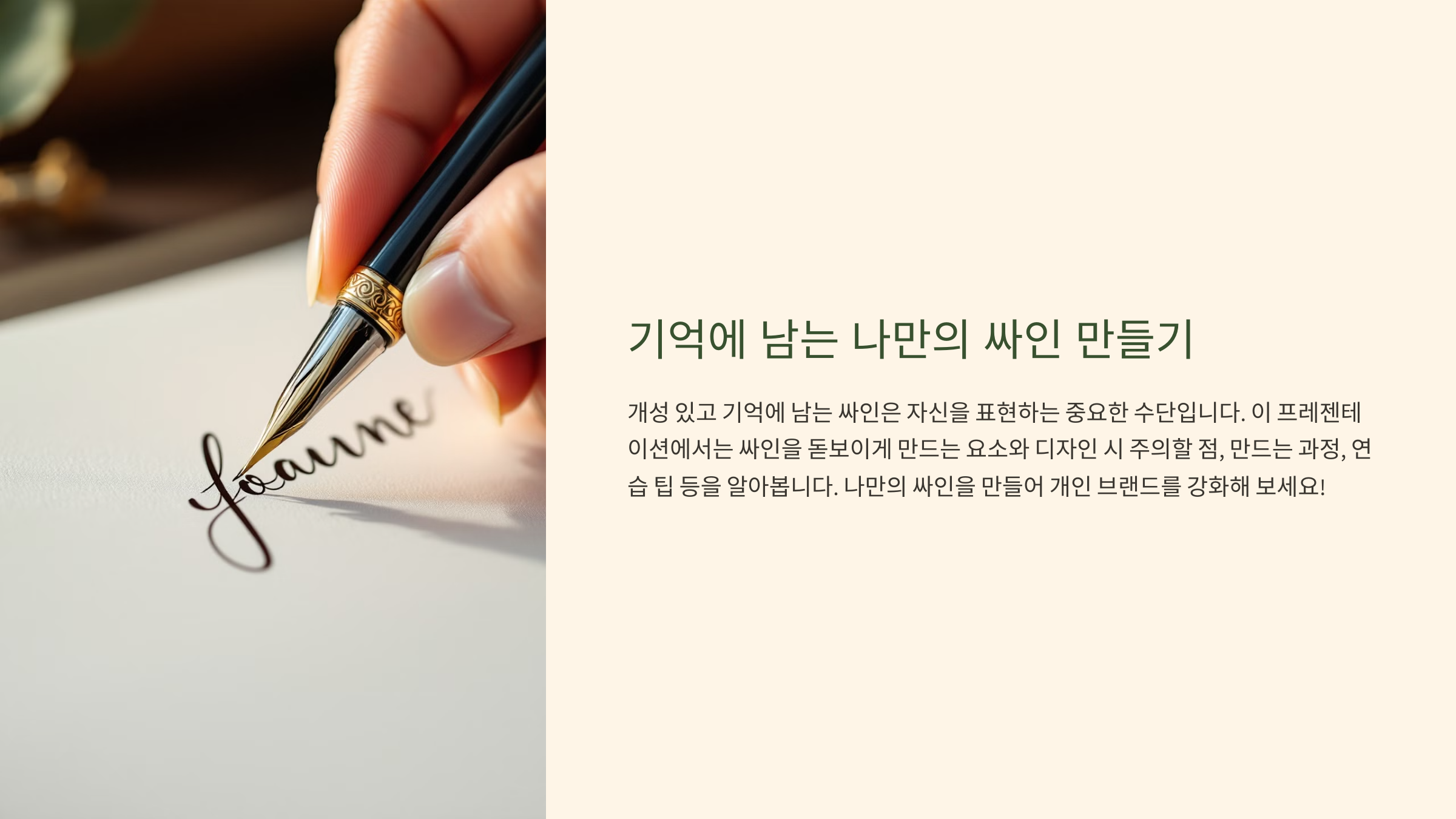
내가 생각했을 때, 기억에 남는 싸인은 단순함 + 개성이 조화를 이루어야 해요. 너무 복잡하면 실전에서 사용하기 어렵고, 너무 단순하면 개성이 부족할 수 있어요. ✍
그럼 한 번 보면 절대 잊히지 않는 싸인 디자인 비법을 배워볼까요? 🚀
기억에 남는 싸인의 특징 🖊
멋진 싸인은 한 번 보면 쉽게 잊히지 않아야 해요! 단순한 서명이 아니라, 나를 대표하는 상징적인 디자인이 되어야 하죠. 🌟🔹 단순하지만 강렬한 디자인 너무 복잡하면 기억하기 어렵고, 실전에서 빠르게 싸인하기 힘들어요. 짧고 간결하면서도 개성 있는 스타일을 유지하는 것이 중요해요.
🔹 독창적인 요소 포함 이니셜을 변형하거나, 기호(하트❤, 별⭐, 번개⚡ 등)를 추가하면 더 특별한 느낌을 줄 수 있어요. 🎨
🔹 자연스럽고 부드러운 흐름 싸인은 너무 뻣뻣하게 만들면 오히려 쓰기 어려워요. 자연스럽게 이어지는 필기체 스타일이 더욱 효과적이에요. ✍
📌 기억에 남는 싸인의 핵심 요소 🔍
요소 설명 단순한 구조 복잡하지 않고 짧고 간결해야 함 독창적인 요소 이니셜 변형, 기호(⭐,❤ 등) 추가 자연스러운 흐름 필기체 스타일로 부드럽게 연결 한눈에 알아볼 수 있음 너무 복잡하지 않고 명확한 형태 유지 이제 싸인을 더 돋보이게 만드는 요소를 알아볼까요? ✨
싸인을 더 돋보이게 만드는 요소 ✨
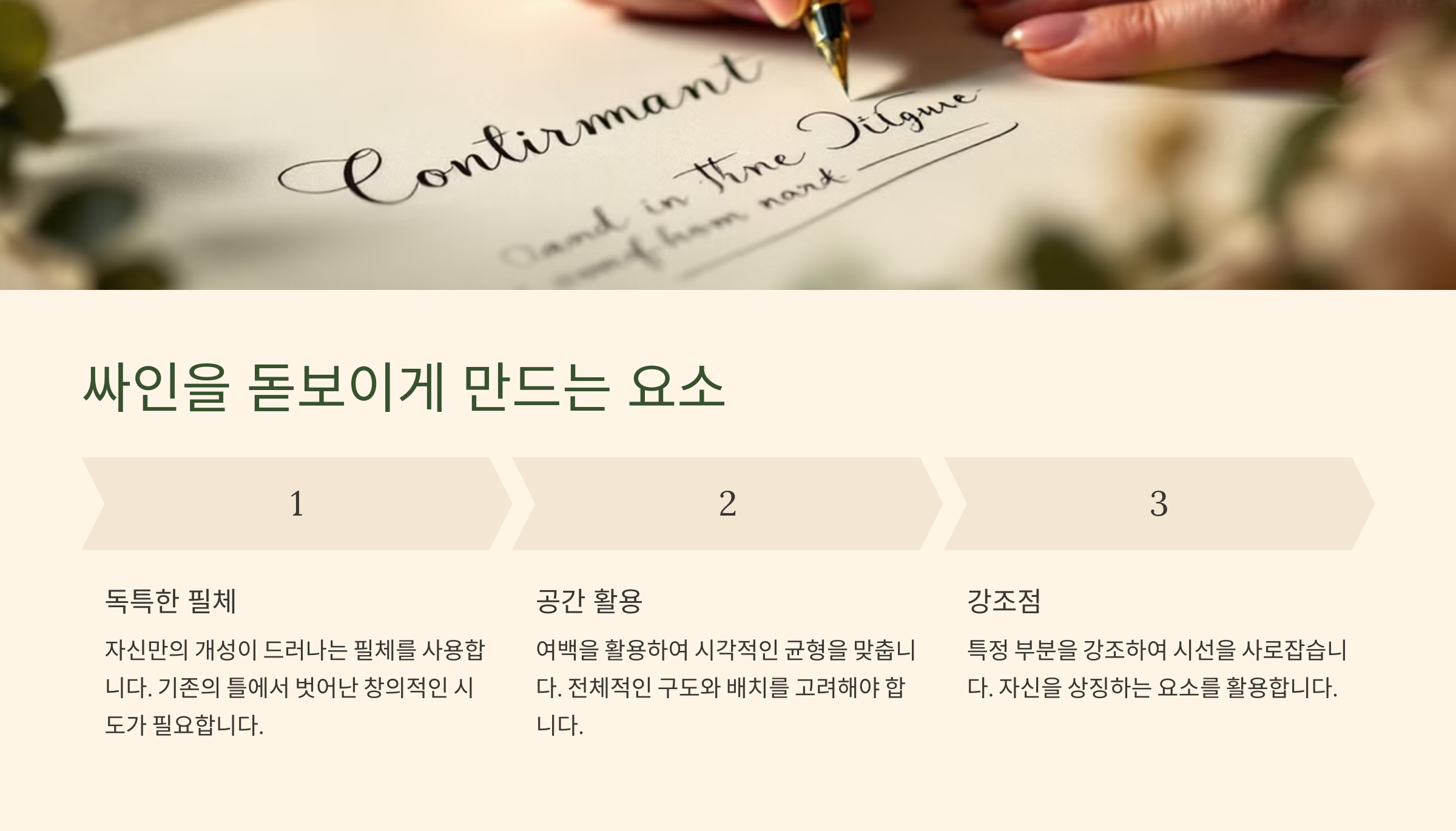
멋진 싸인은 단순히 이름을 쓰는 것이 아니라, 하나의 디자인 작품처럼 개성을 담아야 해요. 작은 차이만 줘도 싸인의 분위기가 완전히 달라질 수 있어요! 🎨🔹 이니셜을 강조하라! 이름 전체를 쓰기보다 이니셜을 변형하면 더 강렬한 인상을 남길 수 있어요. 예를 들어, ‘J.K’처럼 간단하게 정리하면 기억하기 쉬워요.
🔹 특별한 기호 추가하기 하트❤, 별⭐, 화살표➡ 같은 심볼을 싸인에 포함하면 개성이 더욱 살아나요! BTS 멤버들의 싸인처럼 간단한 아이콘을 추가해도 효과적이에요. ✍
🔹 속도감과 자연스러움 유지하기 싸인은 빠르게 써야 할 때가 많아요! 너무 복잡하면 실전에서 사용하기 힘드니, 필기체를 활용해 부드럽고 자연스럽게 연결해 보세요. ⏳
📌 싸인을 더욱 특별하게 만드는 요소 💡
요소 설명 이니셜 강조 이름 대신 첫 글자만 강렬하게 표현 기호 추가 하트❤, 별⭐, 화살표➡ 등 개성 표현 속도감 빠르게 써도 알아볼 수 있는 디자인 자연스러운 흐름 필기체 활용하여 부드럽게 연결 이제 실제로 기억에 남는 스타일별 싸인 예시를 살펴볼까요? 🔎
스타일별 기억에 남는 싸인 예시 🔎
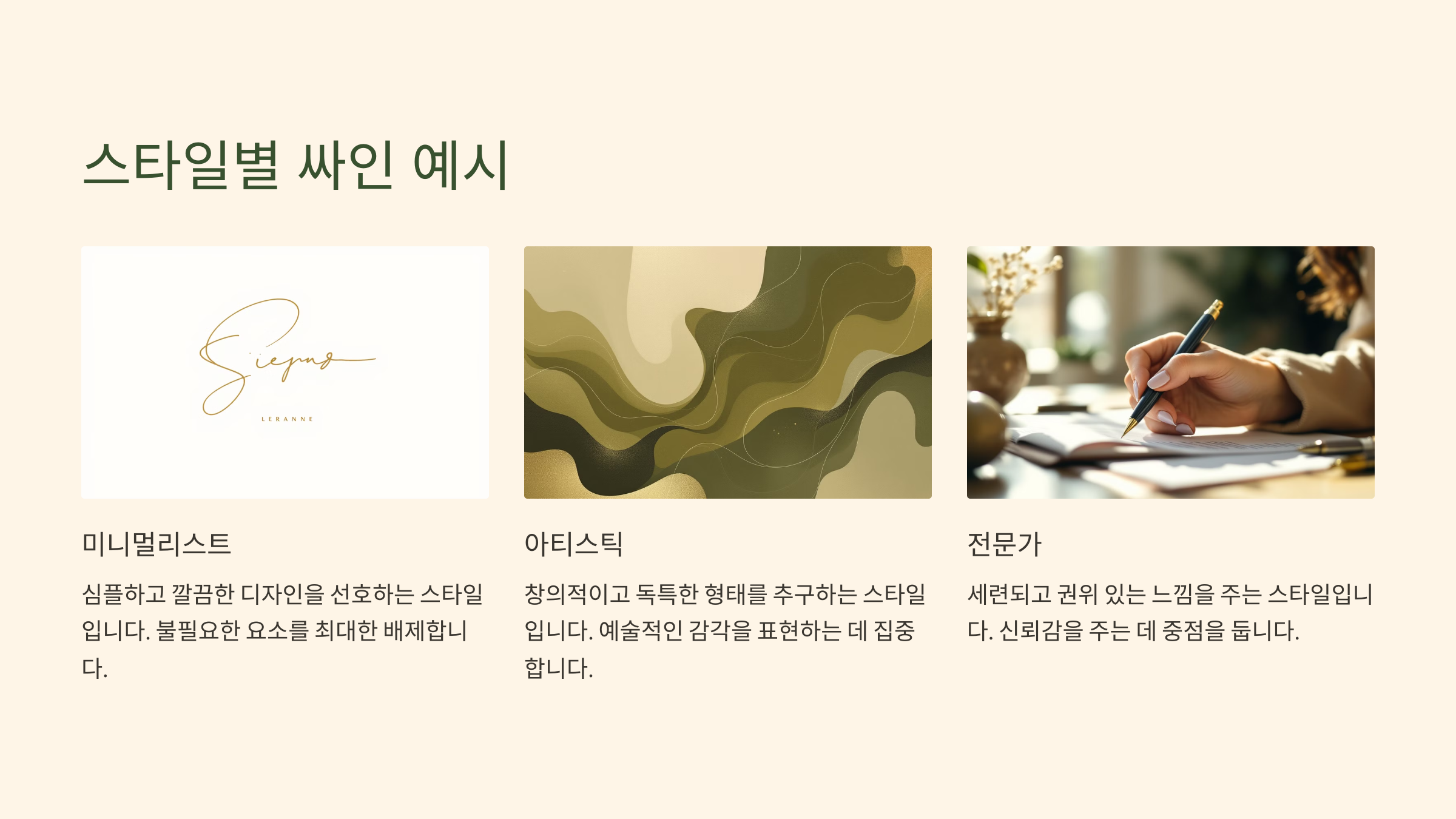
싸인의 스타일은 사람마다 다 달라요. 어떤 스타일을 선택하느냐에 따라 분위기와 인상이 확 달라질 수 있죠. 아래 스타일별 싸인 예시를 보면서 나에게 맞는 스타일을 찾아보세요! ✍
🔹 이니셜형 싸인 이름 전체를 쓰는 대신, 이니셜만 강조하는 스타일이에요. 예를 들어, 'J.H.', 'T.S.', 'RM' 같은 간결한 싸인이 여기에 속해요. ✅ 깔끔하고 세련된 느낌을 주고, 빠르게 싸인할 수 있어요.
🔹 필기체형 싸인 자연스럽게 흐르는 필기체 스타일이에요. 테일러 스위프트의 싸인처럼 부드럽고 우아한 느낌을 줄 수 있어요. ✅ 서명이 필요한 공식 문서에서 활용하기 좋아요.
🔹 그래픽형 싸인 싸인 속에 작은 그림 요소(별⭐, 하트❤, 번개⚡ 등)가 들어가 있는 스타일이에요. 예를 들어, G-DRAGON의 싸인은 독특한 기호와 곡선을 활용해 더욱 개성이 강해요. ✅ 연예인이나 아티스트들이 많이 사용하는 스타일!
📌 스타일별 기억에 남는 싸인 예시 📜
스타일 특징 추천 대상 이니셜형 짧고 강렬한 인상, 간결한 디자인 비즈니스 전문가, 공문서 서명 필기체형 부드럽고 우아한 흐름, 자연스러움 예술가, 디자이너, 작가 그래픽형 개성 넘치는 그림 요소 포함 연예인, 크리에이터, 인플루언서 이제 싸인을 디자인할 때 주의해야 할 점을 살펴볼까요? ⚠
싸인 디자인 시 주의할 점 ⚠
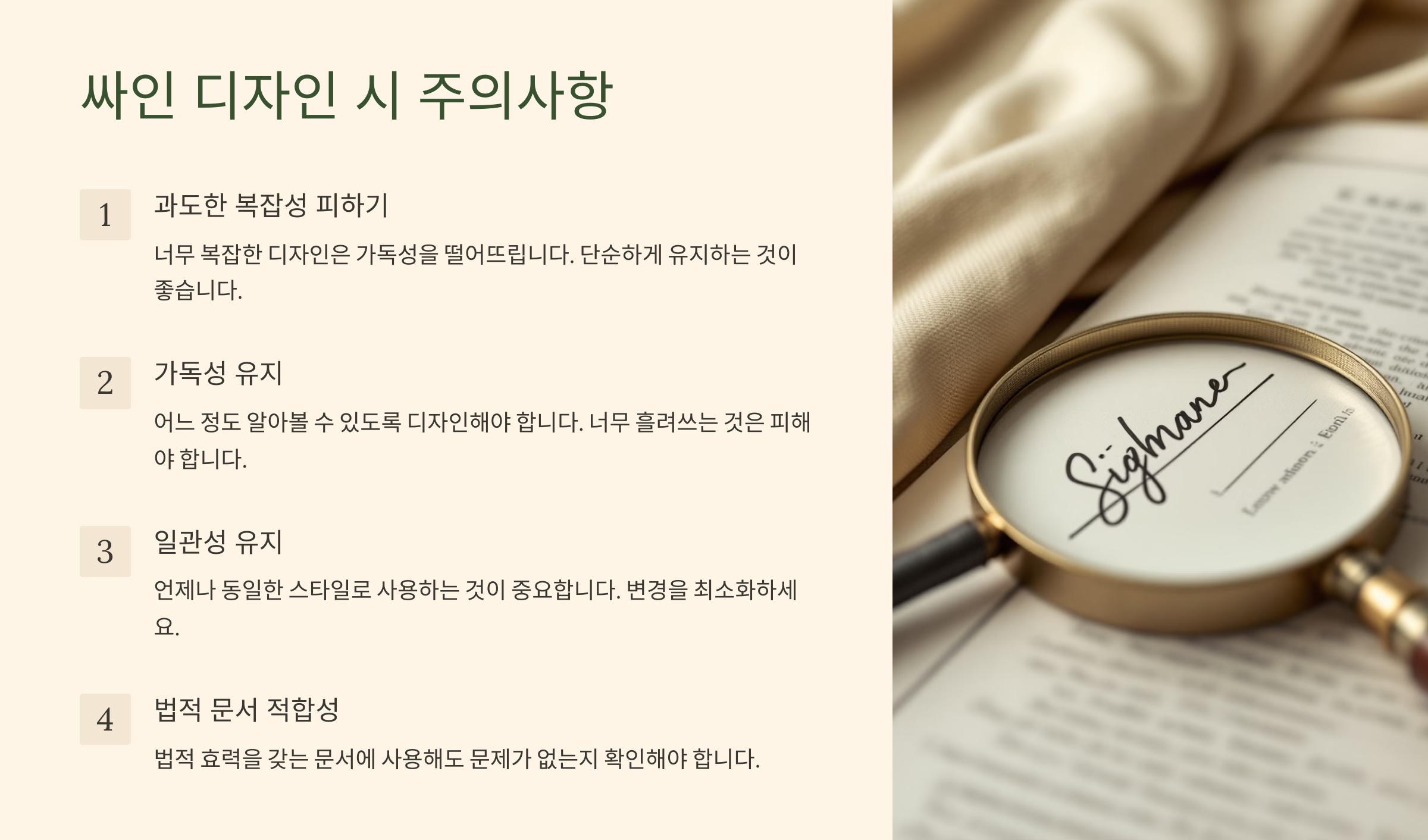
멋진 싸인을 만들기 위해서는 주의해야 할 몇 가지 요소가 있어요. 디자인이 너무 복잡하거나, 실용성이 떨어지면 오히려 불편할 수 있죠! ✍
🔹 너무 복잡한 싸인 피하기 디자인이 지나치게 복잡하면 빠르게 싸인하기 어렵고, 인쇄 시 잘 보이지 않을 수도 있어요. ✅ 단순하면서도 개성이 있는 것이 중요해요!
🔹 읽기 어려운 글씨체 지양하기 너무 독특한 필체를 사용하면 다른 사람이 알아보기 어렵거나, 본인조차 나중에 알아보기 힘들 수도 있어요. ✅ 적당히 알아볼 수 있는 디자인이 좋아요.
🔹 너무 작은 싸인은 피하기 싸인이 너무 작으면 공식 문서나 계약서에서 제대로 보이지 않을 수도 있어요. ✅ A4 용지, 명함, 메모지 등에 테스트하면서 적절한 크기를 찾아보세요.
📌 싸인 디자인 시 피해야 할 실수 ❌
실수 설명 복잡한 디자인 너무 많은 선과 기호를 사용하면 읽기 어려움 읽기 어려운 글씨 너무 기울이거나 변형하면 알아보기 힘듦 너무 작은 크기 공식 문서에서 잘 보이지 않을 가능성 있음 일관성 부족 싸인할 때마다 모양이 달라지는 문제 발생 이제 기억에 남는 싸인을 만들기 위한 5단계 과정을 알아볼까요? 🏆
기억에 남는 싸인 만드는 5단계 과정 🏆
한 번 보면 기억에 남는 싸인을 만들기 위해서는 단계별로 체계적인 연습이 필요해요! 이제 아래 5단계 과정을 따라 하면 나만의 개성 있는 싸인을 완성할 수 있어요. ✍
🔹 1단계: 기본 형태 정하기 이름을 풀네임으로 쓸지, 이니셜을 강조할지 먼저 결정하세요. ✅ 'J.Kim'처럼 짧고 강렬한 스타일이 좋을 수도 있어요.
🔹 2단계: 스타일 선택하기 필기체, 직선형, 곡선형 등 원하는 스타일을 선택하세요. ✅ 자연스럽게 연결되는 필기체 스타일이 기억에 남기 좋아요.
🔹 3단계: 기호 & 장식 추가하기 별⭐, 하트❤, 번개⚡ 같은 작은 기호를 넣어 싸인에 개성을 더해보세요. ✅ 너무 많은 기호를 넣으면 복잡해 보일 수 있으니 적절히 활용!
🔹 4단계: 크기와 속도 테스트 A4 용지, 명함, 메모지 등 다양한 크기에 싸인을 연습하면서 크기를 조절해 보세요. ✅ 싸인이 빠르게 써도 자연스럽게 보이도록 연습하는 게 중요해요!
🔹 5단계: 꾸준히 연습하기 최종적으로 선택한 스타일을 반복 연습하세요. 일관된 형태를 유지하는 것이 중요해요! ✅ 눈 감고 싸인을 해보거나, 빠르게 써보면서 실전 감각을 익혀보세요. ⏳
📌 기억에 남는 싸인 만드는 5단계 과정 🎯
단계 연습 방법 1단계 이름을 풀네임 또는 이니셜 중 선택 2단계 필기체, 곡선형 등 원하는 스타일 결정 3단계 별⭐, 하트❤ 같은 기호를 추가할지 결정 4단계 다양한 크기와 속도로 싸인 테스트 5단계 최종 스타일을 정하고 반복 연습 이제 싸인 연습을 더 효과적으로 할 수 있는 실전 꿀팁을 알아볼까요? 🚀
싸인 연습을 위한 실전 꿀팁 🚀
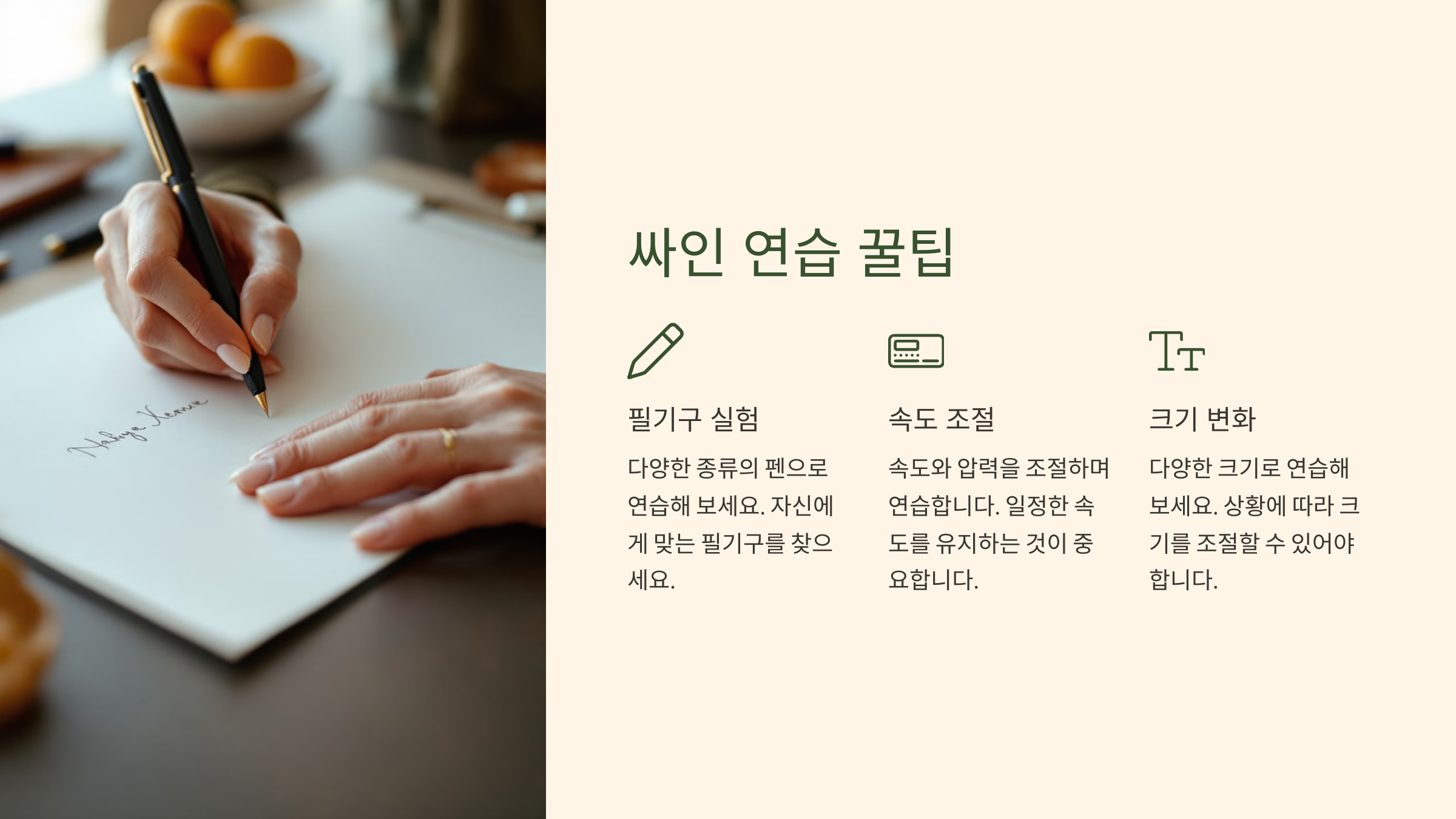
싸인은 단순히 디자인하는 것보다, 실제로 빠르게 싸인을 할 수 있도록 연습하는 과정이 중요해요! 아래 실전 꿀팁을 따라 하면 더욱 자연스럽고 멋진 싸인을 만들 수 있어요. ✍
🔹 거울을 보면서 연습하기 싸인을 하면서 거울을 통해 보는 시각도 중요해요. 다른 사람이 봤을 때 어떤 느낌인지 체크해보세요. 👀
🔹 눈 감고 싸인해보기 눈을 감고 싸인을 해보면 손이 자연스럽게 기억하는 싸인을 만들 수 있어요. ✅ 익숙해질 때까지 감각적으로 연습해보세요!
🔹 속도 조절하며 연습하기 너무 천천히 하면 실전에서 시간이 오래 걸리고, 너무 빠르면 알아보기 어려울 수 있어요. ✅ 적절한 속도를 찾으면서 연습해보세요. ⏳
🔹 다양한 크기로 싸인해보기 A4 용지, 명함, 포스트잇 등에 싸인을 연습하며 적절한 크기와 두께를 조절해보세요. ✅ 실전에서 어디서든 사용할 수 있도록 준비!
📌 싸인 연습을 위한 실전 꿀팁 🎯
연습 방법 설명 거울을 보며 연습 다른 사람이 봤을 때의 느낌 체크 눈 감고 싸인하기 손이 기억하는 자연스러운 싸인 완성 속도 조절하며 연습 빠르게 써도 알아볼 수 있는 스타일 찾기 다양한 크기로 연습 A4, 명함, 포스트잇 등 다양한 크기 테스트 이제 싸인에 대한 궁금증을 해결할 시간! FAQ에서 자주 묻는 질문을 정리해볼까요? ❓
FAQ ❓
Q1. 기억에 남는 싸인을 만들려면 가장 중요한 요소는 무엇인가요?
A1. 가장 중요한 요소는 간결함과 개성이에요. 싸인은 너무 복잡하면 빠르게 쓰기 어렵고, 너무 단순하면 개성이 부족할 수 있어요. 짧지만 강렬한 디자인이 기억에 남기 좋아요. ✍
Q2. 싸인에 기호(하트, 별 등)를 넣으면 좋은가요?
A2. 네! 작은 기호를 활용하면 개성이 강조되고, 더욱 특별한 싸인이 될 수 있어요. 하지만 너무 많은 기호를 넣으면 오히려 복잡해 보일 수 있으니 적절히 활용하는 것이 좋아요. ⭐❤⚡
Q3. 싸인 연습을 할 때 가장 효과적인 방법은?
A3. 반복적인 연습이 필수예요! 먼저 원하는 스타일을 정한 후, 1) 눈 감고 써보기 2) 다양한 크기로 연습하기 3) 빠른 속도로 써보기 이런 방식으로 연습하면 자연스럽고 멋진 싸인을 만들 수 있어요. 🚀
Q4. 싸인 스타일을 정할 때 고려해야 할 점은?
A4. 실용성과 디자인을 모두 고려해야 해요. - 공식 문서에서도 사용할 수 있도록 너무 장식적인 싸인은 피하기 - 싸인의 속도감과 가독성을 고려하기 - 개성 있는 요소(이니셜, 기호 등)를 추가하기 이런 점을 고려하면 더 효과적인 싸인을 만들 수 있어요. 🎨
Q5. 싸인을 자주 바꾸면 문제가 될까요?
A5. 싸인은 일관성이 중요해요. 문서 서명이나 계약서에 싸인을 할 때 매번 다르면 신뢰도가 떨어질 수 있어요. 한 번 정한 싸인을 꾸준히 유지하는 것이 좋아요! 🖊
Q6. 한글 싸인과 영어 싸인 중 어떤 것이 더 좋을까요?
A6. 용도에 따라 달라요. - 한글 싸인: 개성이 강하고 독창적인 느낌을 줄 수 있어요. - 영어 싸인: 글로벌한 이미지와 간결한 디자인을 만들기 좋아요. 자신의 필요에 따라 선택하는 것이 가장 좋아요! ✅
Q7. 싸인을 너무 크게 하면 안 되나요?
A7. 싸인의 크기는 적절해야 해요. 너무 크면 문서에 서명할 때 불편하고, 너무 작으면 알아보기 어려울 수 있어요. A4, 명함, 포스트잇 등 다양한 크기로 연습하면서 최적의 크기를 찾는 것이 중요해요. 📏
Q8. 싸인을 바꾸면 운이 바뀐다는 말이 있던데, 사실인가요?
A8. 과학적인 근거는 없지만, 싸인을 바꾸면 자신감과 이미지가 달라지는 효과가 있어요. 특히, 성공한 사람들의 싸인을 보면 개성이 뚜렷한 경우가 많아요! 💯
이제 기억에 남는 싸인을 만들 준비가 끝났어요! 꾸준한 연습을 통해 나만의 멋진 싸인을 완성해보세요. 🚀✨